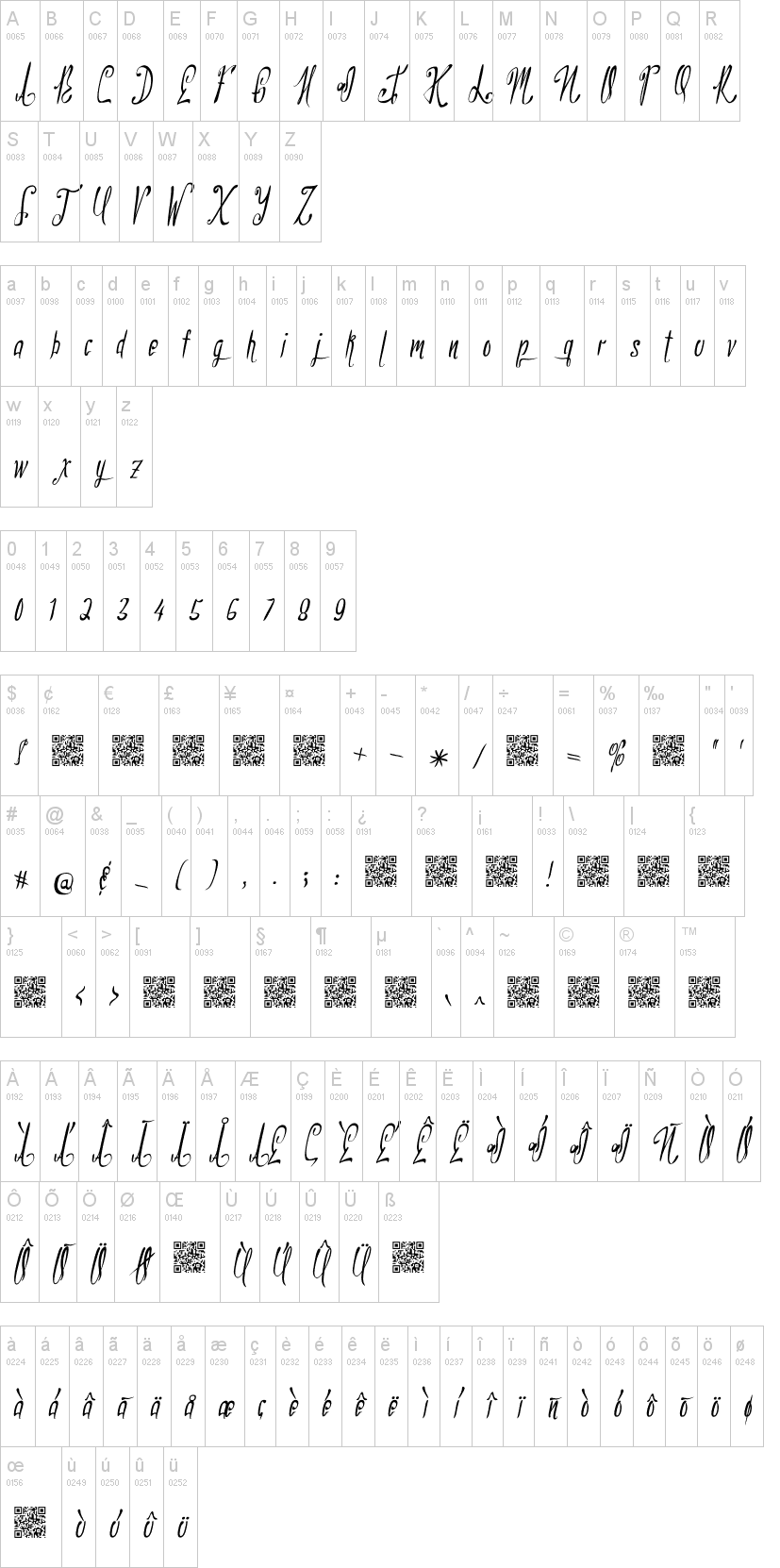
Northern Montgomery是一款简洁优雅的英文字体,由英国设计师James Montalbano设计。它的设计风格具有极强的英式风格,整体显得优雅大方。字体的外观极具现代感,细节处理精致,有助于提升文本的可读性。此外,它还具有良好的空间感,可以在多种尺寸的文本中使用,并且可以非常容易地调整字体大小,以满足不同的需求。内容介绍
Northern Montgomery是一款非常不错的手写艺术字体,具有很好的视觉感,适合于文化类的宣传设计、商业类品牌的广告和产品包装设计以及个性化文字排版等较多场景。